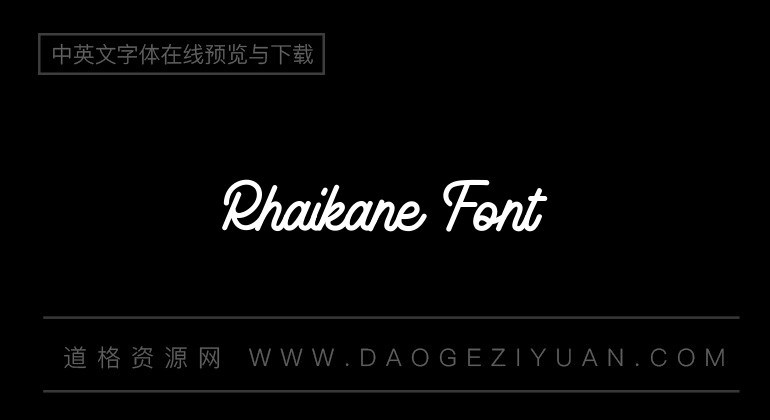
Rhaikane Font 是一种免费的手写风格字体,由设计师Youssef Habchi创建。该字体具有手写风格,因此适用于许多用途,如标志、海报、卡片等。 该字体具有不规则的线条和个性化的笔画,使其看起来很自然。它由大写和小写字母、数字和标点符号组成,可用于多种语言。 Rhaikane Font 提供了两个版本:正常和粗体。它们都可以免费下载,且无需许可证即可用于商业和个人项目。内容介绍
Rhaikane Font是一款非常不错的手写艺术字体,具有很好的视觉感,适合于文化类的宣传设计、商业类品牌的广告和产品包装设计以及个性化文字排版等较多场景。